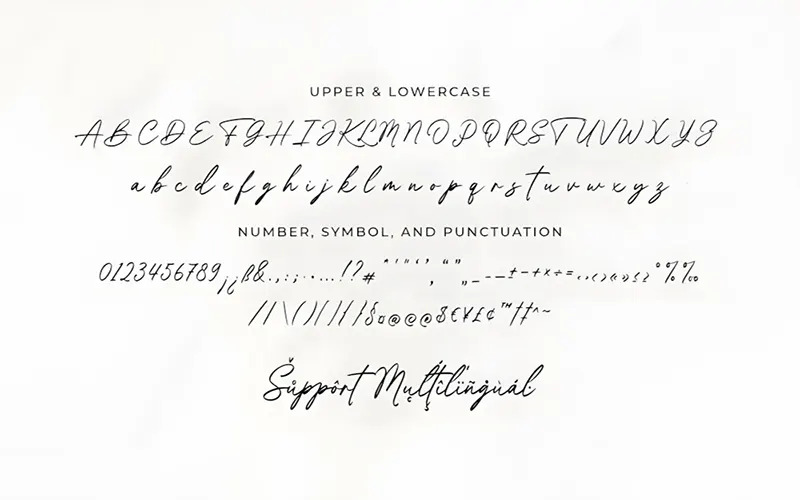
Font chữ kéo dài là gì và sức hút trong đồ họa?
Font chữ kéo dài, hay còn gọi là font chữ có đuôi (Swash fonts), là những bộ phông nghệ thuật với các nét chữ được thiết kế vươn dài, uốn lượn bay bổng ở điểm đầu hoặc điểm cuối. Đặc trưng của dòng font kéo dài này là khả năng khơi gợi cảm xúc tinh tế, sang trọng và đầy tính cá nhân hóa. Đây là công cụ đắc lực để tạo điểm nhấn thị giác, giúp các dòng tiêu đề trở nên mềm mại và có sức sống hơn hẳn các phông chữ cơ bản thô cứng.
Trong xu hướng thiết kế hiện đại, font chữ viết tay kéo dài được ưa chuộng nhờ vẻ đẹp thủ công nhã nhặn. Các đường tà chữ bay bổng không chỉ giúp xóa bỏ khoảng cách giữa các ký tự mà còn tạo nên một tổng thể nhịp nhàng như những dải lụa. Vì vậy, phông chữ này thường xuất hiện trong các bộ nhận diện thương hiệu cao cấp, từ nhãn hàng chăm sóc sắc đẹp đến các dòng thực phẩm tự nhiên, mang lại cảm giác thân thiện và tin cậy cho người tiêu dùng.
05 Ứng dụng phổ biến của font chữ kéo dài trong thực tế
Vẻ đẹp thanh thoát của các mẫu chữ kéo dài giúp nâng tầm giá trị cho nhiều ấn phẩm truyền thông của doanh nghiệp:
- Nâng tầm bao bì sản phẩm mỹ phẩm: Sử dụng font chữ kéo dài đuôi để in ép kim trên nắp hộp giấy Ivory hay hộp cứng. Những đường nét thanh mảnh giúp lớp vỏ bọc sản phẩm trông bắt mắt, thu hút khách hàng ngay từ cái nhìn đầu tiên.
- Thiết kế ấn phẩm sự kiện sang trọng: Đây là họa tiết linh hồn cho các mẫu backdrop, thiệp mời VIP hay voucher tri ân. Định dạng vector sắc nét đảm bảo các dải chữ uốn lượn mềm mại, mang lại cảm giác trang trọng cho buổi lễ.
- Gia công in UV, khắc laser trên hiện vật lưu niệm: Hình ảnh biểu trưng được in trên bình giữ nhiệt kim loại, sổ tay bìa da hoặc sạc dự phòng. Độ sắc sảo của file giúp phông chữ hiển thị rõ ràng trên mọi bề mặt, tạo dấu ấn khác biệt.
- Sản xuất bộ tem nhãn niêm phong tinh tế: Các mẫu Font chữ viết tay kéo dài được dùng để làm sticker dán túi giấy thời trang hoặc tem nhãn hũ thực phẩm chức năng, giúp bộ nhãn dán trở nên sinh động và độc đáo.
- Đồng bộ bộ nhận diện văn phòng: Sử dụng phông chữ này cho các slogan trên phong bì thư hay kẹp file giúp thương hiệu của bạn toát lên vẻ tinh tế, chuyên nghiệp và có gu thẩm mỹ cao trong mắt đối tác.
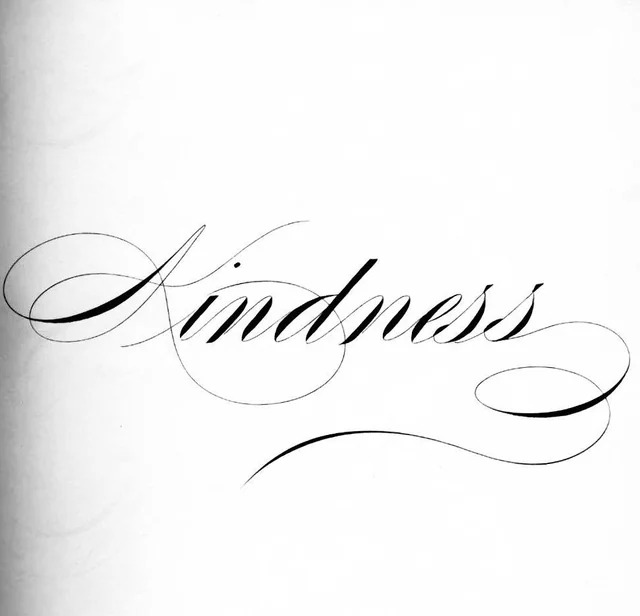
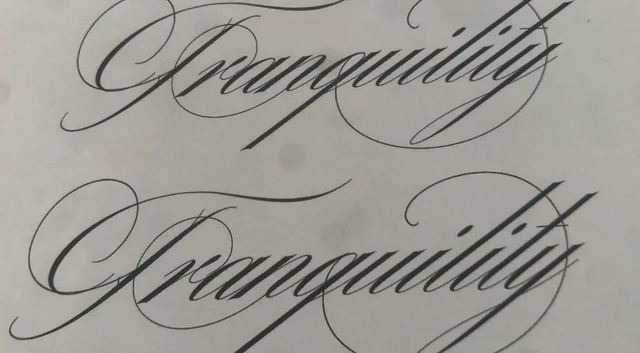
04 lưu ý kỹ thuật khi sử dụng font chữ kéo dài Việt hóa
Để hệ thống ký tự nghệ thuật hiển thị sống động và bền màu trên các thành phẩm thực tế, designer cần chú trọng các quy tắc sau:
- Kiểm soát độ dày nét thanh: Các mẫu font kéo dài thường có phần đuôi mảnh. Khi in ấn kích thước nhỏ, designer nên tăng nhẹ độ dày Stroke để mực bám ổn định, tránh tình trạng nét chữ bị đứt đoạn hay mờ nhòe.
- Tối ưu đường Path cho gia công bế nổi: Khâu này đặc biệt quan trọng khi sản xuất vỏ hộp cao cấp dập nổi biểu tượng. Việc làm mượt các điểm neo trong file thiết kế giúp khuôn bế thực hiện chính xác, tránh hiện tượng rách giấy mỹ thuật tại các góc hẹp.
- Xử lý các điểm giao ký tự: Khi các đuôi chữ chồng lấn nhau, bạn nên sử dụng tính năng nối liền các mảng màu trong phần mềm đồ họa. Việc này đảm bảo mực in được trải đều và không xuất hiện các vết hằn đậm nhạt thiếu tự nhiên.
- Thiết lập hệ màu CMYK chuẩn: Phông chữ nghệ thuật thường đi kèm với sắc vàng đồng hoặc đỏ. Designer cần hiệu chỉnh hệ màu chuẩn và yêu cầu xưởng in mẫu thử để đảm bảo màu sắc sau in trung thực với bản thiết kế gốc.